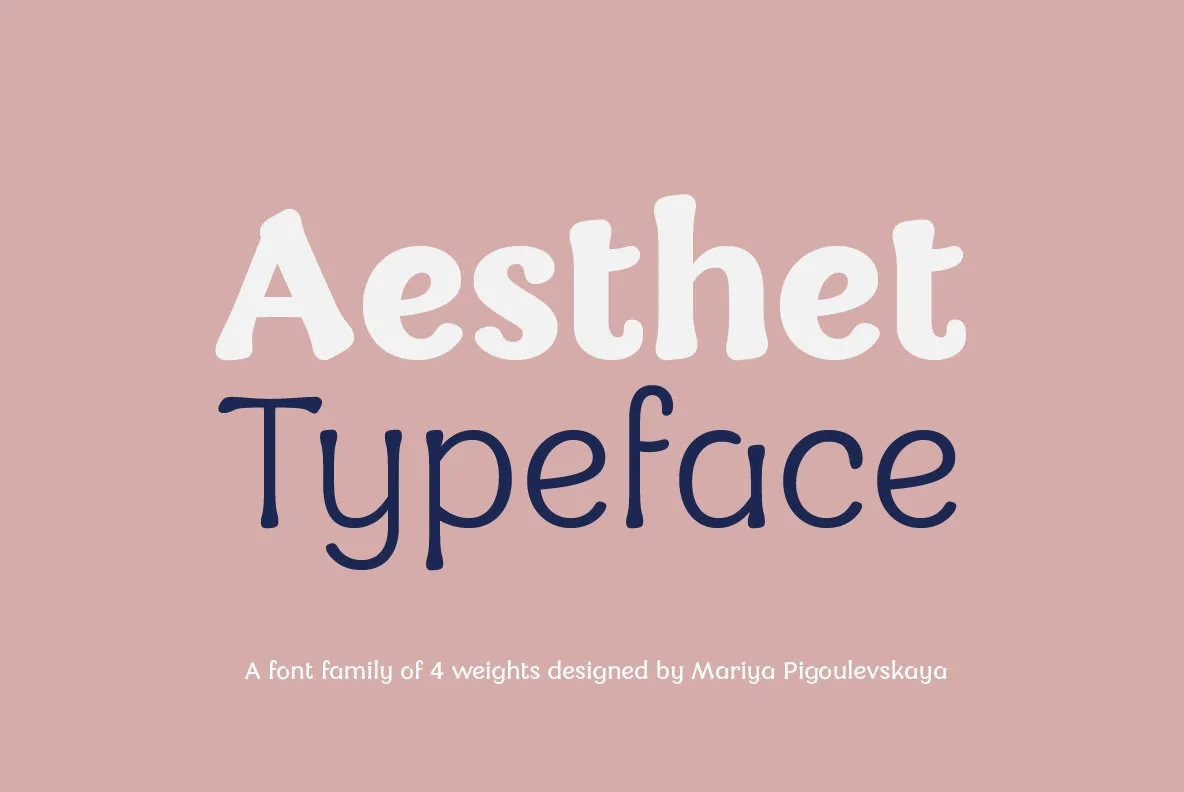
A Aesthet é uma família de tipo sans serif composta por quatro pesos. Inspirada na experiência pessoal de vida rural, essa família reflete a busca por um estilo de vida simples e inspirado no meio ambiente. O projeto foi inspirado por experimentos criativos que mostraram como o handmade pode evoluir em relação aos tipos convencionais. A Aesthet foi projetada para destacar-se em tamanhos maiores, tornando-a uma escolha atraente para headlines. Em tamanhos menores, os detalhes exagerados ganham menos importância sem comprometer a qualidade do texto. Uma das características únicas da Aesthet é o número total de caracteres contidos nessa família: 380, incluindo as funções avançadas do OpenType e ajustes personalizados de kerning. Esta fonte não apenas oferece uma aparência distinta em tamanhos maiores, mas também preserva a essência natural em formatos menores. É perfeita para aqueles que buscam uma conexão com o meio ambiente ao criar materiais digitais. A Aesthet é a escolha ideal para designers buscando transpor experiências pessoais e valores ambientais em sua identidade visual digital.